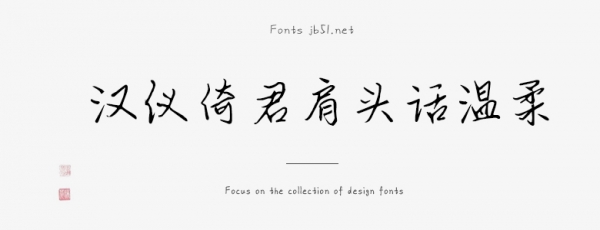
漢儀倚君肩頭話溫柔是由漢儀字庫(kù)出品,字體筆觸詳細(xì),書(shū)寫(xiě)隨心灑脫,具有很好的視覺(jué)感,適合應(yīng)用于藝術(shù)設(shè)計(jì)、平面宣傳設(shè)計(jì)、網(wǎng)頁(yè)設(shè)計(jì),書(shū)法字帖等領(lǐng)域,需要的朋友可以前來(lái)本站下載。